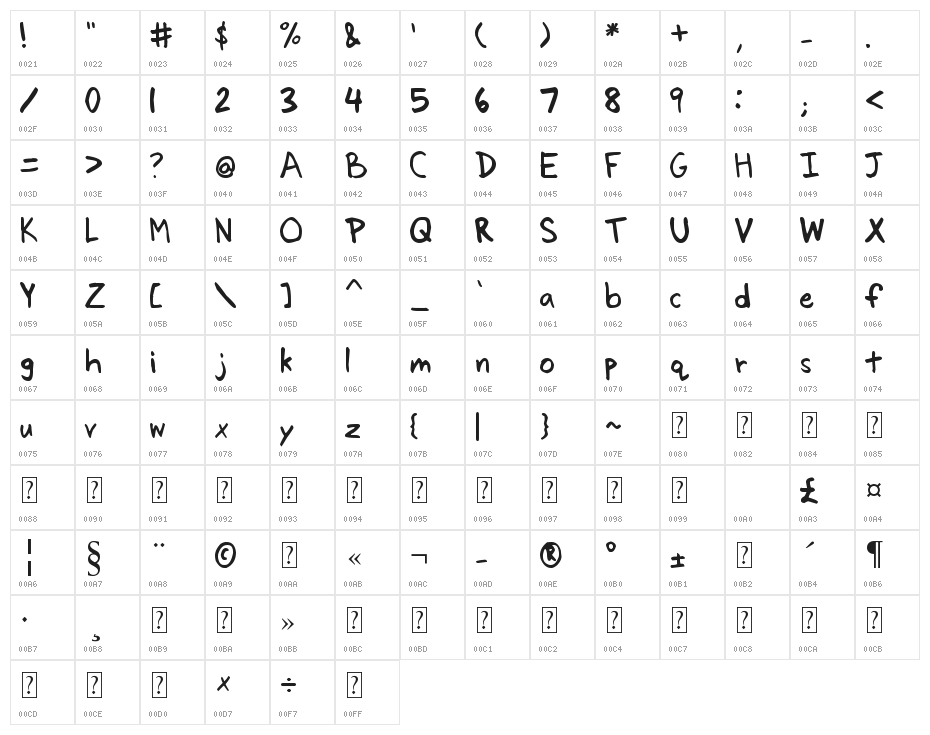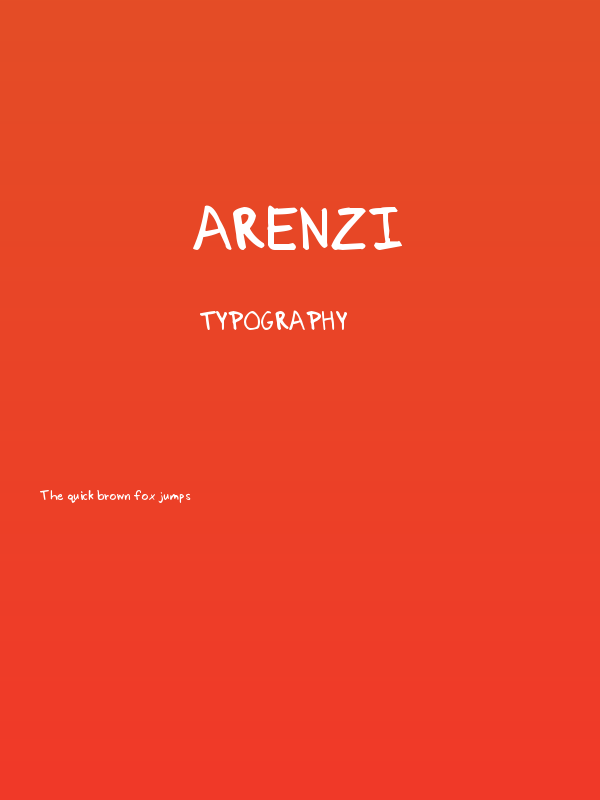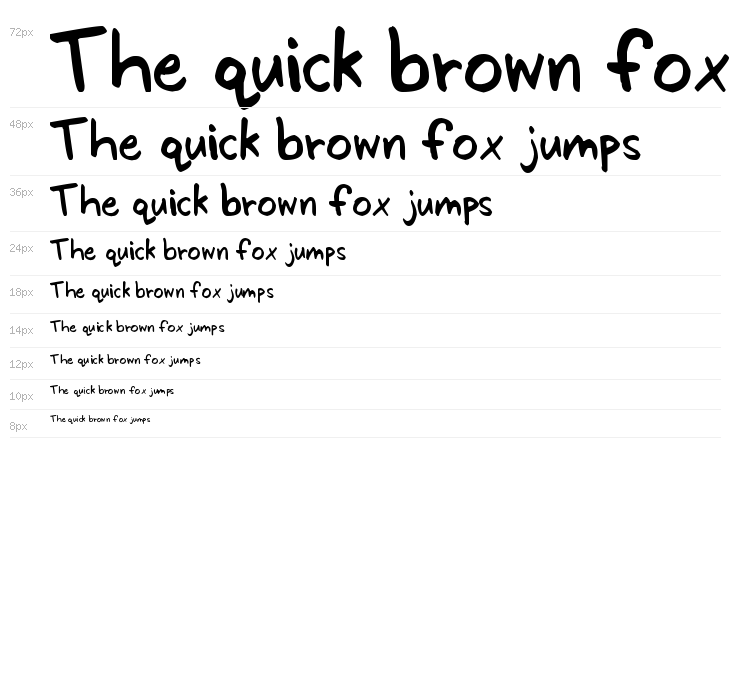
Arenzi Font
✎ Handwritten
| श्रेणियाँ | Handwritten |
| समग्र शैली | Casual |
| उपयोग का मामला | Headlines, Logos, Informal Text |
| सुझाए गए प्रोजेक्ट | Ideal for greeting cards, children's books, playful branding, and social media graphics. |